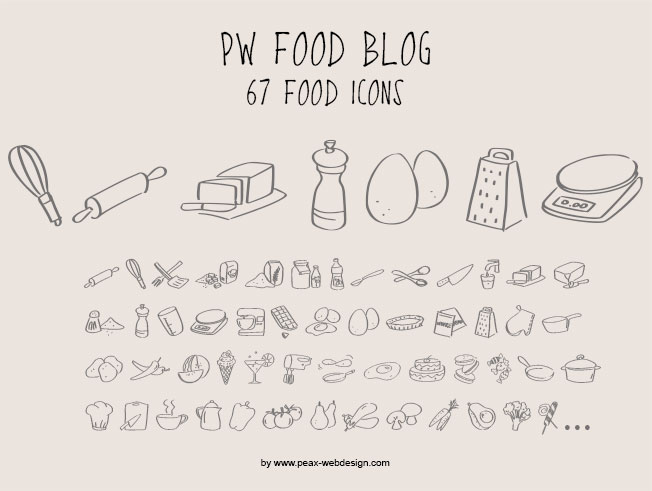
PW Foodblog, police d'icônes culinaires
Que vous teniez un blog culinaire ou que vous soyez simplement à la recherche d'illustrations sur le thème des aliments ou de la cuisine, cette nouvelle police de caractères saura combler vos attentes : 67 icônes sont disponibles en tout , que vous pourrez ensuite personnaliser en les colorisant dans votre logiciel préféré. N' hésitez pas à me montrer vos créas sur https://fr-fr.facebook.com/peax.webdesign ou https://plus.google.com/103595703505477716588 !